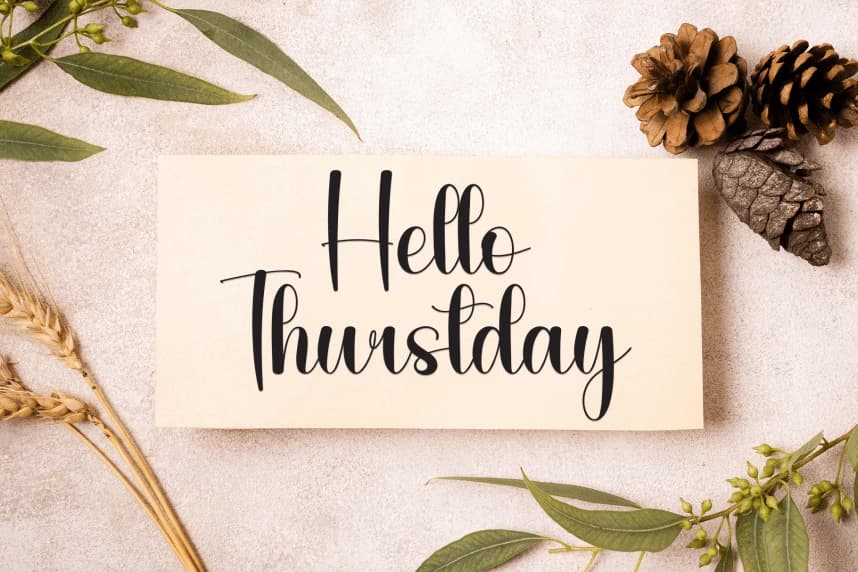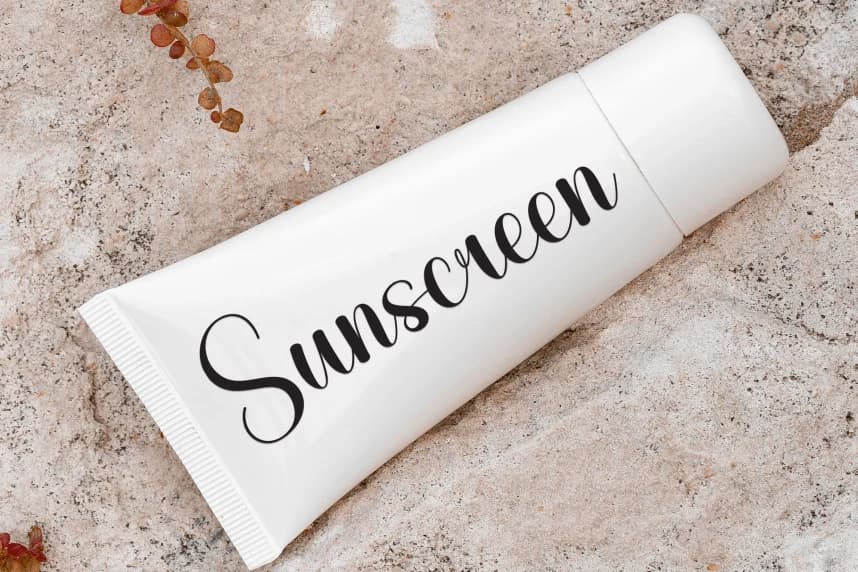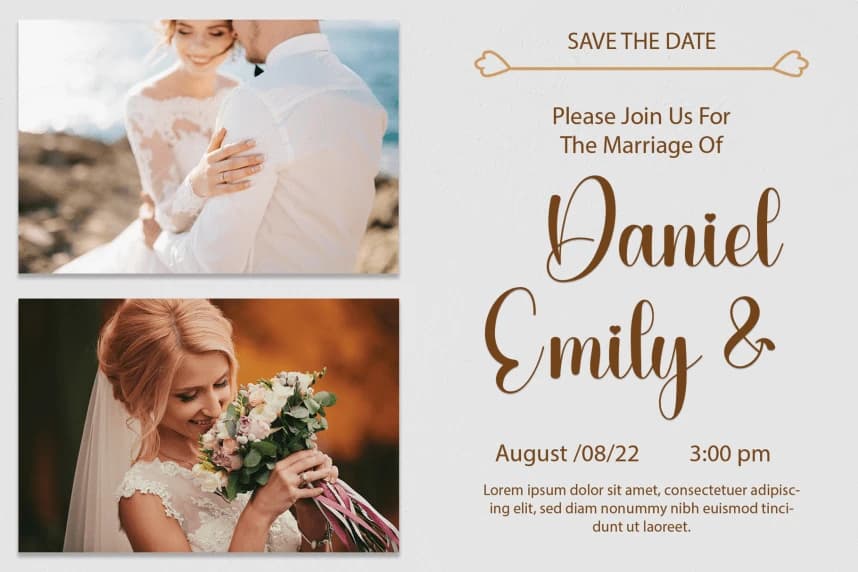
Sunshine – Authentic Handwritten Style Font
Sunshine – Authentic Handwritten Style Font, tatlı ve samimi bir el yazısı gösterim yazı tipidir. Sevimli ve eğlenceli olan bu yazı tipi, düğün davetiyelerini yazmak, kartlar hazırlamak veya eğlenceli bir dokunuşa ihtiyaç duyabilecek diğer tasarımlar için idealdir!
Sunshine – Authentic Handwritten Style Font, tatlı ve samimi bir el yazısı gösterim fontudur. Sevimli ve eğlenceli olan bu font, düğün davetiyelerini, kartları yazmak için veya başka herhangi bir tasarım için eğlenceli bir dokunuşa ihtiyaç duyabileceğiniz projeler için idealdir!
Sunshine – Authentic Handwritten Style